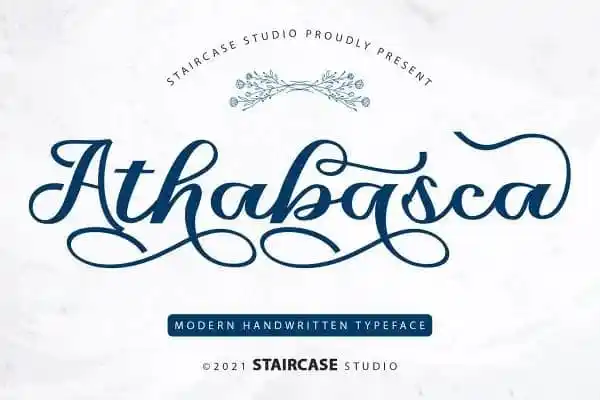
Athabasca Calligraphy Font – Fonte Grátis
Athabasca Calligraphy Font
A Athabasca Calligraphy Font é uma elegante tipografia escrita à mão com um clima contemporâneo e formas perfeitas. Inspirada nas chamadas tradicionais, esta fonte é ideal para projetos que exigem estilo gráfico sofisticado. Desenvolvida pela Staircase Studio na 99designs, ela oferece uma coleção de letras e números perfeitamente ajustados para suas necessidades de design. É perfeita para logotipos, criação de marcas, design de logos, arte digital de letra, t-shirts e roupas, cartazes, magazines, sinalização e publicidade. A Athabasca é uma fonte versátil que atende a qualquer necessidade de design.